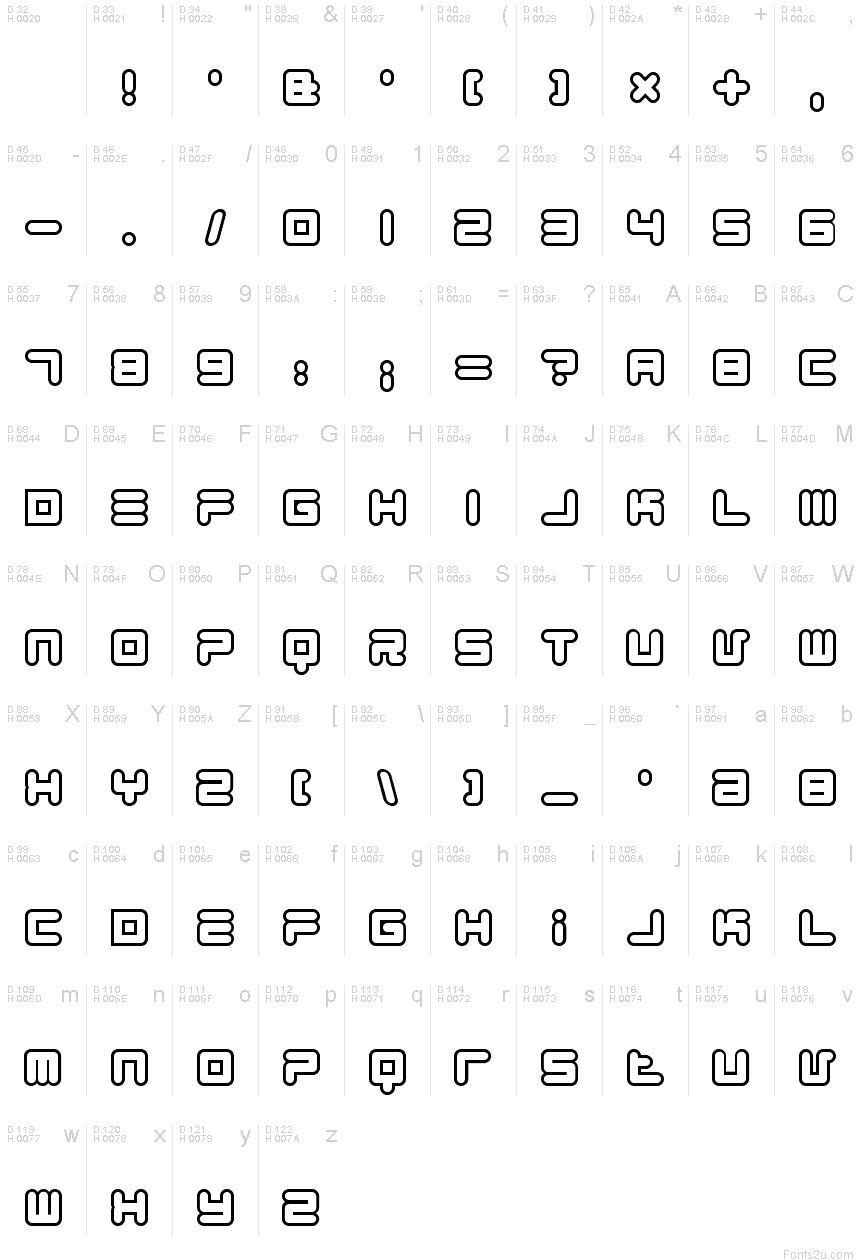
1900.80.5 od dustBUST Fonts to darmowy, nowoczesny krój displayowy typu outline, który wygląda, jakby został wyciągnięty prosto z cyfrowego zegara z innej linii czasu. Zaokrąglone prostokąty, narożniki w kształcie pigułek i jednolita grubość linii nadają każdemu znakowi czystą, tubularną formę, a puste wnętrze pozwala na eksponowanie kolorów, gradientów lub tekstur. Efekt jest wyrazisty i techniczny, ale dzięki miękkim kształtom pozostaje przystępny, unikając ostrej, kanciastej agresywności.
Za pomocą 1900.80.5 sprawisz, że liczby i krótkie słowa przykują uwagę na plakatach sci-fi, w brandingu technologicznym, na ekranach odliczających, w interfejsach UI, tytułach gier czy na okładkach albumów elektronicznych. Ten darmowy font najlepiej sprawdza się w dużych rozmiarach, gdzie jego przestronne kontury mogą „odetchnąć”, i świetnie komponuje się z prostym geometrycznym bezszeryfem w roli tekstu uzupełniającego.